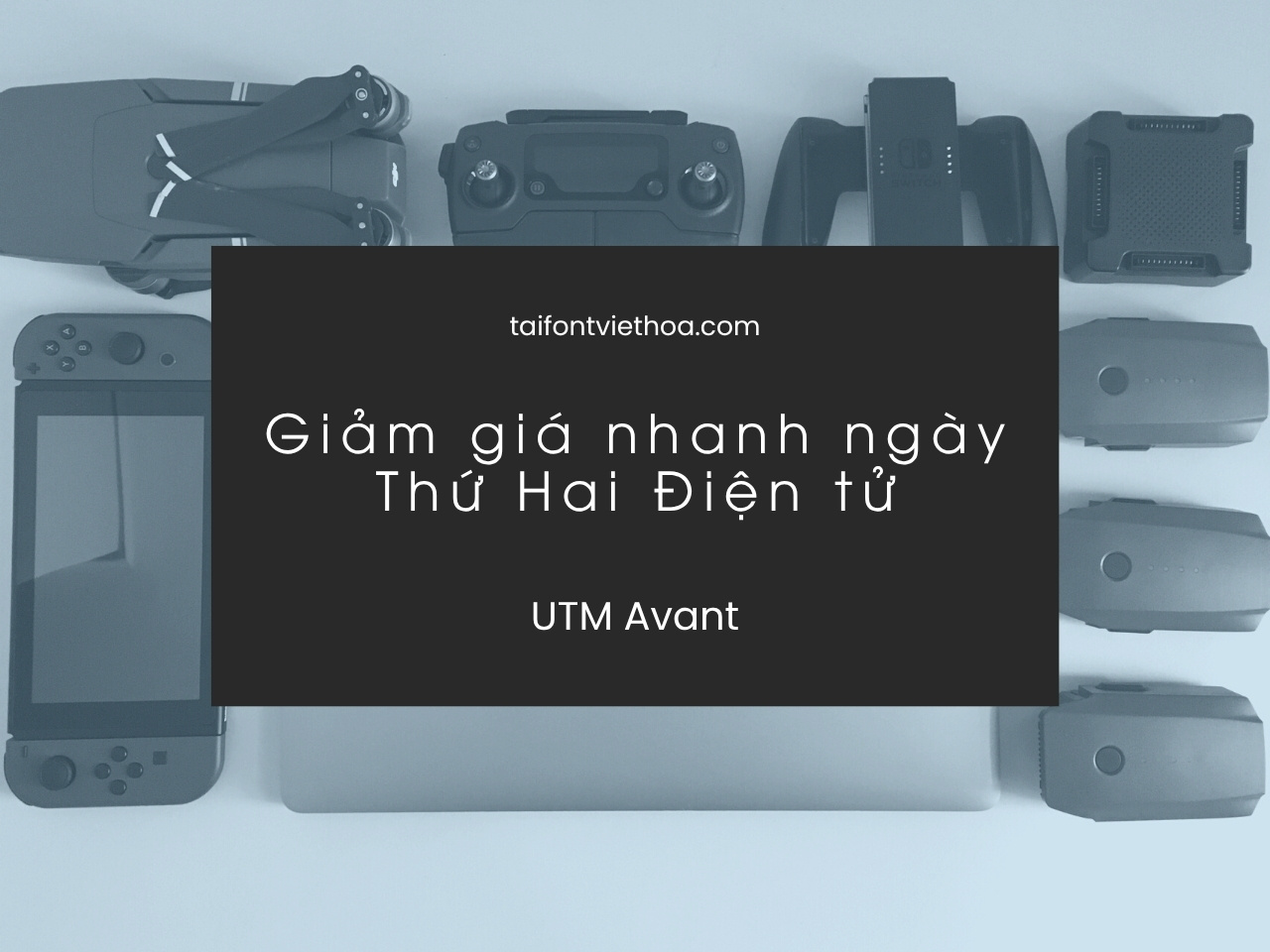
Font việt hóa UTM Avant
Giới thiệu về font UTM Avant
UTM Avant là phiên bản Việt hóa của font Avant – một kiểu chữ sans-serif hiện đại và năng động, được thiết kế bởi nhà thiết kế nổi tiếng tại Châu Âu. Font gốc nổi bật với thiết kế hình học, các nét chữ vuông vức và cấu trúc cân đối, phù hợp cho các dự án thiết kế đòi hỏi sự tối giản và linh hoạt. Phiên bản Việt hóa đã được hoàn thiện để hỗ trợ đầy đủ tiếng Việt cùng hơn 200 ngôn ngữ khác, giúp mở rộng khả năng sử dụng trong nhiều dự án sáng tạo toàn cầu.
Font UTM Avant được taifontviethoa.com sưu tầm và lựa chọn kỹ càng nhằm phục vụ cộng đồng thiết kế Việt Nam. Phiên bản Việt hóa giữ nguyên phong cách hiện đại, tối giản của bản gốc và tối ưu khả năng hiển thị tiếng Việt, phù hợp với nhiều mục đích thiết kế từ thương hiệu đến quảng cáo và truyền thông số.
Đặc điểm thiết kế và ứng dụng của UTM Avant
UTM Avant sở hữu cấu trúc sans-serif không chân, với các nét chữ vuông vức, đồng đều và rõ ràng. Font có độ dày vừa phải, thiết kế tối giản giúp tăng khả năng đọc và linh hoạt trong nhiều kích thước và môi trường hiển thị khác nhau. Font phù hợp cho cả tiêu đề và nội dung văn bản dài, mang lại sự hiện đại và chuyên nghiệp cho các dự án thiết kế.
Font thích hợp sử dụng trong thiết kế website, nhận diện thương hiệu, quảng cáo, bao bì sản phẩm, brochure, và các dự án truyền thông đa phương tiện. Các ngành nghề phù hợp gồm: công nghệ, giáo dục, quảng cáo, startup và thương mại điện tử.